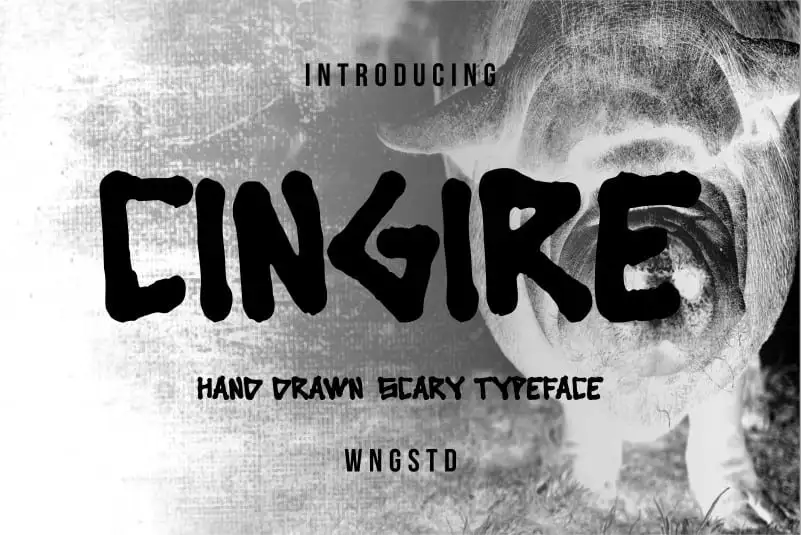
Cingire – Hand drawn scary typeface – Download Grátis
A fonte Cingire é uma mistura divertida de tipo a mão desenhada com traços assustadores. É perfeitamente adequada para uso tanto na mídia tradicional quanto na web, e é perfeita para quem curte fazer arte manual ou trabalhos gráficos. Ela se destaca por sua leveza e personalidade, tornando-a uma escolha ideal para projetos criativos, desde materiais de inspiração até outdoors com temática assustadora. Cingire também oferece flexibilidade em termos de compatibilidade com vários programas de edição de texto. O designer WNGSTD nos oferece a chance de expressar nossa personalidade e transmitir nossa marca de uma maneira única e impactante. Com sua paleta vibrante e estilo desenho a mão, Cingire é o tipo ideal para os amantes do design que querem incorporar um elemento único à sua próxima criação visual.